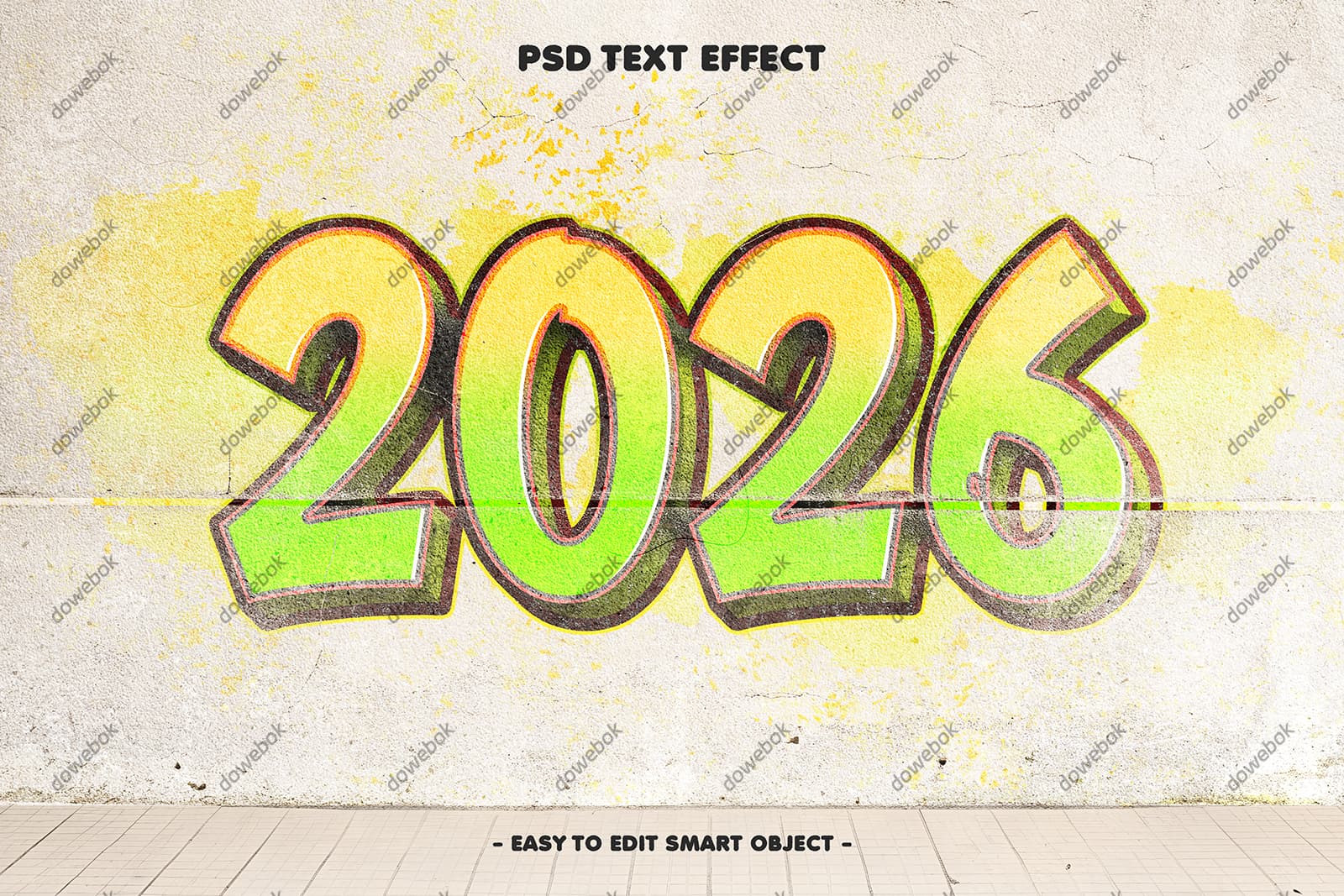
这是一款由渐变涂鸦设计 2026 新年快乐 PSD 素材,斑驳灰白墙面为背景,缀着黄绿泼墨痕迹,“2026” 以黄到绿的渐变涂鸦字体呈现,边缘粗犷具街头质感。顶部标 “PSD TEXT EFFECT”,底部注其为可编辑素材。整体风格随性张扬,涂鸦与泼墨元素结合,既显潮流个性,又点明字体效果的可编辑属性,适配创意海报、潮流物料等场景。